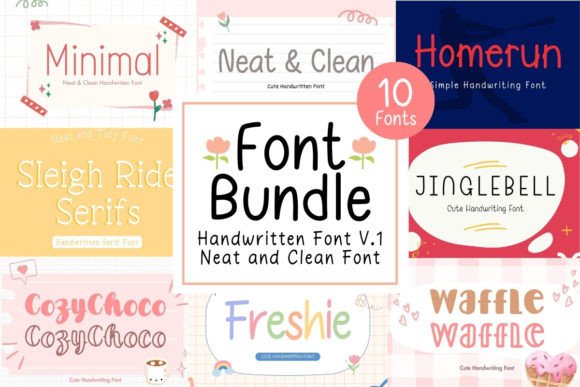
Neat & Clean Handwritten Font Bundle V.1
การค้นหาองค์ประกอบการออกแบบที่เหมาะสมอาจเป็นเรื่องท้าทาย แต่ Neat & Clean Handwritten Font Bundle V.1 นำเสนอคอลเลกชันที่โดดเด่นซึ่งช่วยยกระดับงานของคุณได้ทันที
สร้างขึ้นอย่างแม่นยำ Neat & Clean Handwritten Font Bundle V.1 ให้เวกเตอร์ที่สะอาด พิมพ์ตัวอักษรที่ราบรื่น และใบอนุญาตเชิงพาณิชย์เพื่อความสบายใจ
ไม่ว่าคุณจะสร้างผลิตภัณฑ์ POD (Print on Demand) คำเชิญงานแต่งงาน หรือกราฟิกโซเชียลมีเดีย Neat & Clean Handwritten Font Bundle V.1 ก็เหมาะสมอย่างยิ่ง